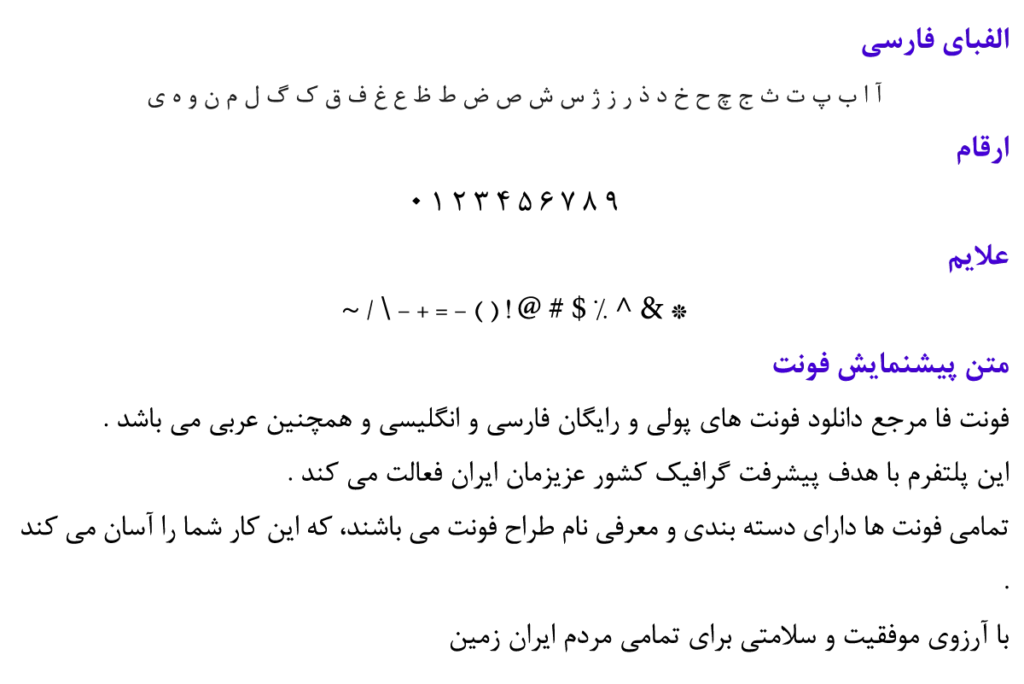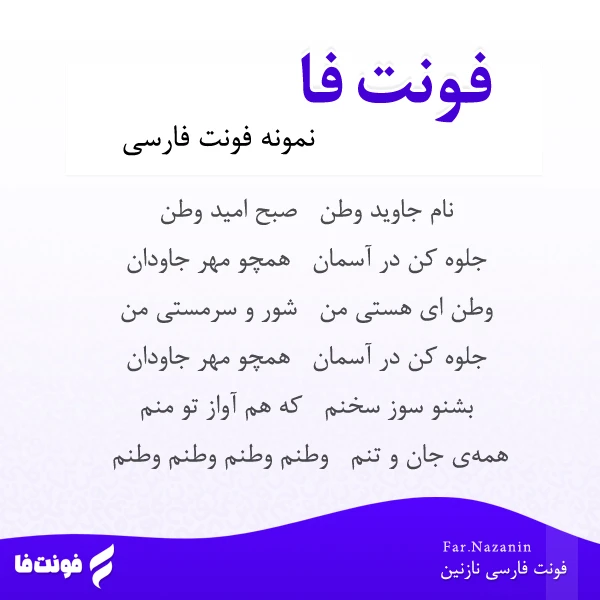
فونت فارسی نازنین – Far Nazanin
طراح فونت: ابوالفضل سيل سپور نوع فونت: فونت متن
توضیحات و معرفی فونت نازنین
فونت فارسی نازنین ( Far Nazanin ) از مجموعه فونت های سری Far می باشد، همچنین نوع فونت متن می باشد.
فونت فوق العاده زیبای معرفی شده توسط ابوالفضل سيل سپور در سال 1390 طراحی و ساخته شده است.
در تصویر زیر میتونید شعر زیبای نام جاوید وطن را ببینید که با این تایپ فیس زیبای فارسی طراحی شده است.